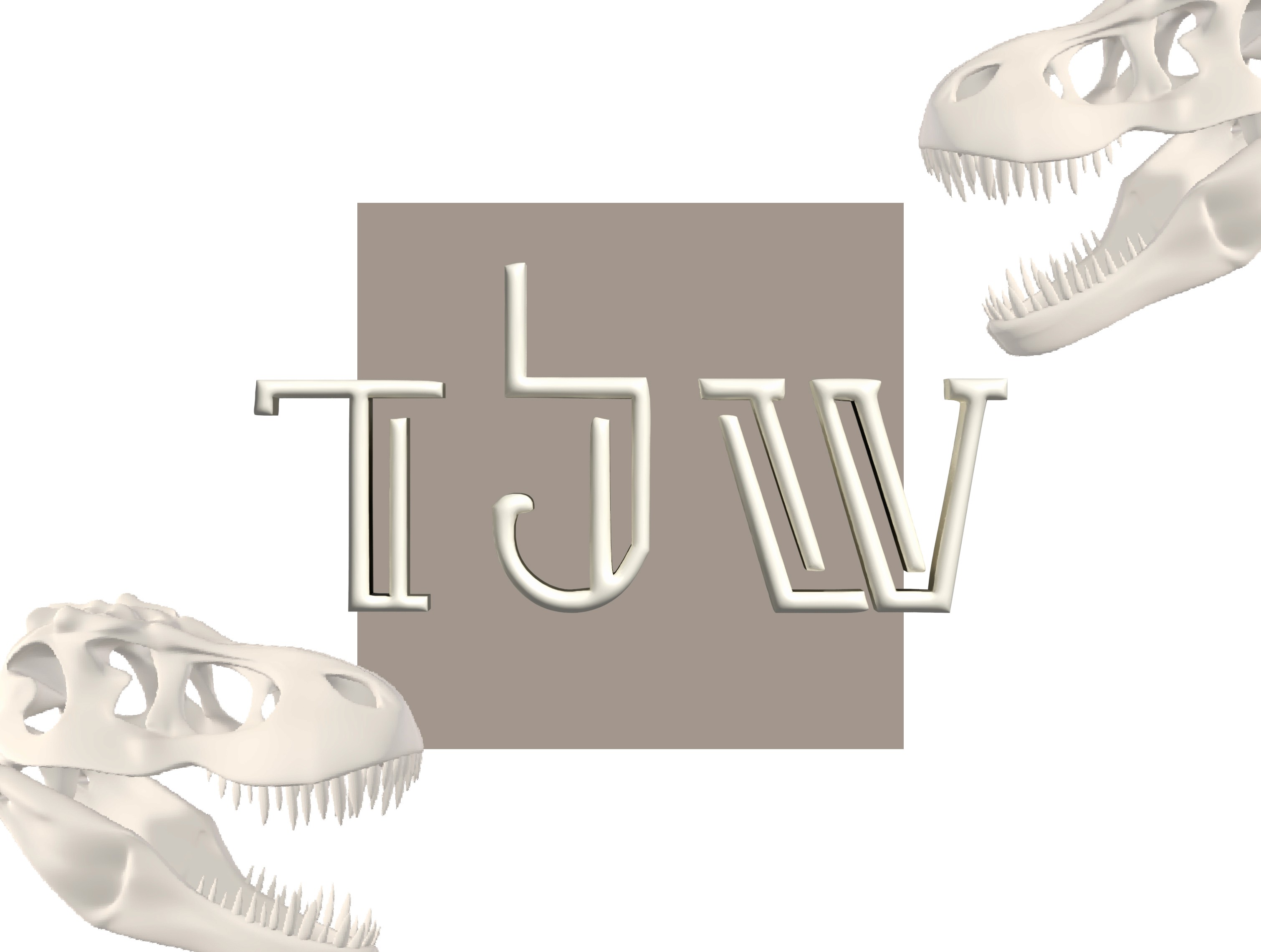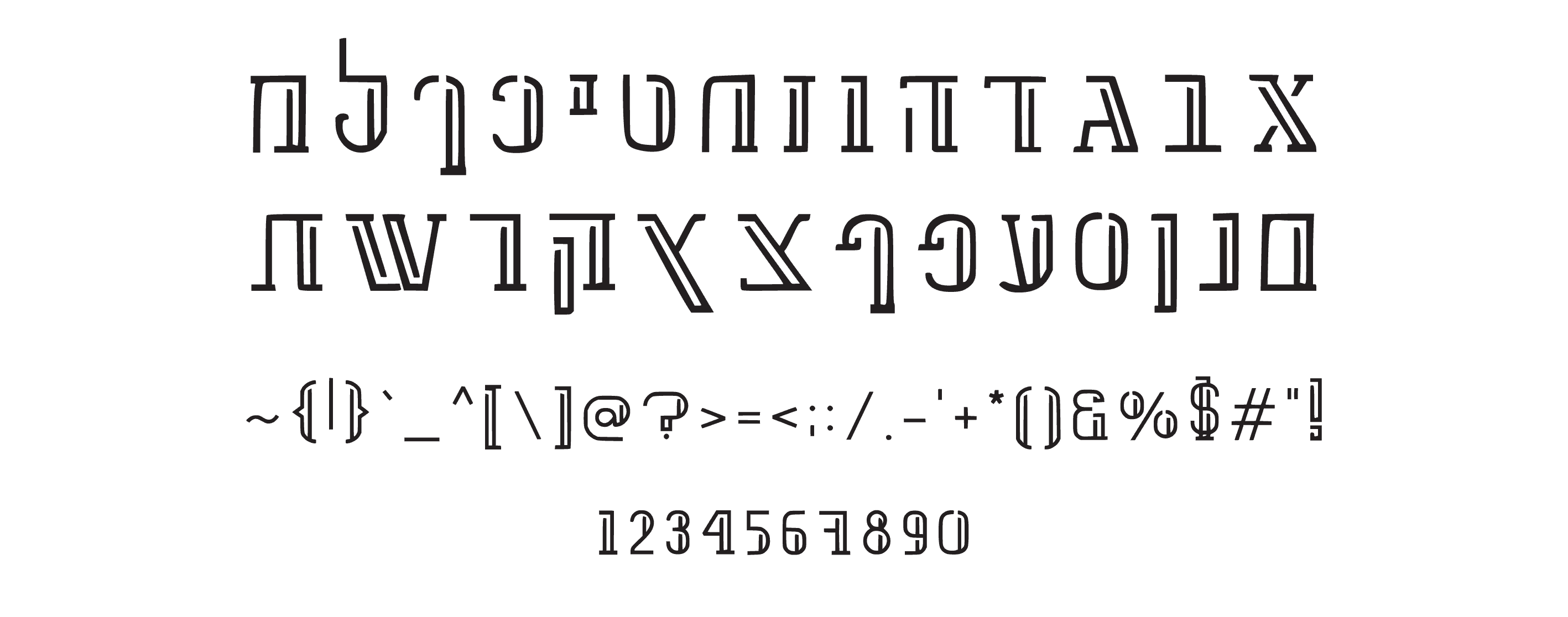
פונט שלד
פונט עברי דקיק וגרפי בסגנון שלד, מושלם לפוסטרים אמנותיים ולוגואים אלטרנטיביים.
שלד — הפונט שנוגע בעצמות של העיצוב
לא כל פונט נועד להיות נעים, עגלגל או פשוט לקריאה.
שלד הוא פונט גרפי, מינימליסטי ומורכב, שמציג את קווי המתאר של האותיות — כמו שלד חשוף.
יש בו תחושת מסתורין, תחכום ואסתטיקה לא שגרתית.
הוא מתאים למעצבים שחושבים אחרת — כאלה שרוצים להעניק לעיצוב שלהם מראה שונה, מדויק, גאומטרי ואקספרסיבי.
הפונט הזה מתבלט בכל מקום שבו רוצים ליצור אמירה עיצובית חזקה וייחודית, כזו שאי אפשר להתעלם ממנה.
איפה הוא מרגיש בבית?
🦴 פוסטרים אמנותיים ונועזים
🦴 לוגואים למותגים אלטרנטיביים
🦴 עיצובים אורבניים ומחתרתיים
🦴 הדפסים לחנויות עיצוב, גלריות ואירועי תרבות
למי הוא מתאים?
למעצבים אמנותיים, מותגים מחתרתיים, וחובבי עיצוב שאוהבים קווים חדים, גיאומטריים ומלאי אופי.